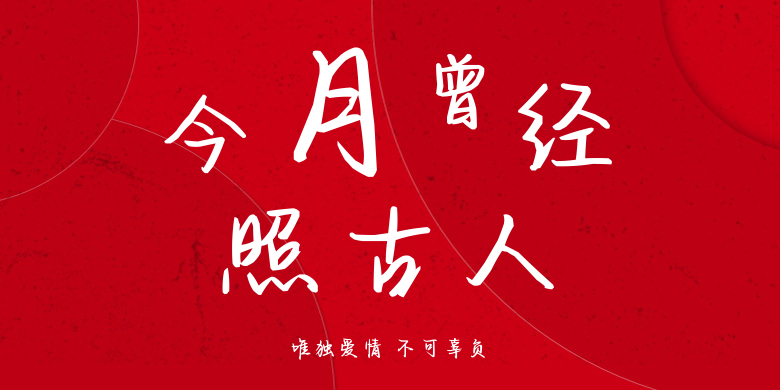
唯独爱情 不可辜负
唯独爱情 不可辜负,这款字体结构工整、笔画清晰,兼顾美观与易读性,适用于标题、正文、海报、包装、LOGO 等多种场景。字形优雅稳定,风格百搭耐看,适配日常排版与创意设计,让文字呈现更舒适、更具质感。唯独爱情 不可辜负一笔一画,皆是细节,以均衡的比例、流畅的线条打造舒适视觉体验,字形端正大气,风格简约现代。无论是商业设计、品牌宣传还是日常排版,都能轻松驾驭,让文字更有格调与力量。唯独爱情 不可辜负字体下载。